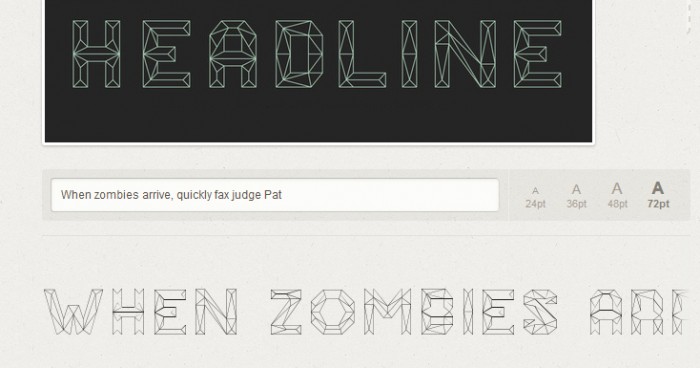
Schlechte Vorschau
nachdem mein letztes Problem hier so schnell gelöst wurde, muss ich heute noch einmal eure Hilfe in Anspruch nehmen.
Es geht immer noch um meinen Polygon-Font. Soweit funktioniert jetzt alles, sowohl in verschiedenen Programmen, im Druck, auf PC und Mac. Darum wollte ich ihn nun endlich zum Download bereit stellen und dann sieht die Vorschau so aus, wie auf dem Bild (unterer Bereich)....
Waagerechte Linien brechen zum Teil komplett weg und das in allen verfügbaren Punktgrößen. Da es auch andere Schriften mit ähnlich dünnen Linien gibt, die in der Vorschau gut funktionieren, vermute ich mal, dass es ein Fehler bei mir ist. Aber bisher konnte mir noch keiner sagen, woran es liegen könnte.
Das ist einfach eine Frage des Hinting, unds das ist bei diesem Font einfach zu kompliziert für ein automatisches Hinting, der Rechner erkennt einfach nicht, welche Konturen er, im Falle, das sie nicht genau aufs Pixelraster passen, germeinsam eher nach oben oder untenn schieben soll. Hierdurch wird dsann eben nicht eigentlichg zusammengehörige Vektoren gemeinsam verschoben, sondern einzeln auf das Pixelraster gerundet.
Um das jetzt ideal hin zu bekommen, muss man dem Rechner über händis eingegebene Anweisungen erklären, velche Vektoren gepaart sein müssen.
Solch ein Hintig ist aber letztlich eine deutlich aufwändigere Sache, als die Zeichnung der Font-Outlies selbst.
Oh je, das hört sich ja nach einer schwer lösbaren Aufgabe an... Dann werde ich das Ding wohl nur als Vektorfont anbieten. Aber vielen Dank für die Antwort catfonts!
Die Schrift ist doch gerade zu perfekt für automatisches Hinting: nur gerade lange Linien. Wenn sauber gearbeitet wurde und Linien, die gleich breit sein sollten, auch wirklich gleich breit sind, sollte hier überhaupt kein Problem bestehen (und auch bei leichten Abweichungen nicht). Ähnliches gilt für das automatische Finden von BlueValues.
Eigentlich sollten alle Linien in etwa dieselbe sStärke haben. Ich habe sie, wie gesagt, alle in Illustator mit derselben Linienstärke angelegt, in Flächen umgewandelt und dann per Hand auf das Raster angepasst. Ich werde sie noch einmal genau unter die Lupe nehmen und mal versuchen, das Autohinting wegzulassen. Wenn ich eine Lösung gefunden habe, werde ich sie hier posten. Danke schon mal für die Tipps!
Nebenbei würde ich mir den Font bgerne mal ansehen. Vielleicht fällt mir ja eine praktikable Lösung ein.
Ich werde sie noch einmal genau unter die Lupe nehmen und mal versuchen, das Autohinting wegzulassen.
Wieso das? Das Autohinting Deines Schrifterstellungsprogramms kann wahrscheinlich mit wenig Arbeit Deine Probleme lösen. Alles, was Du tun musst, ist es laufen zu lassen und ggf. einige Parameter anpassen, damit etwas Vernünftiges dabei rumkommt.
Danke, catfont! TTF-Autohinting hat geklappt. Jetzt bin ich glücklich. :)